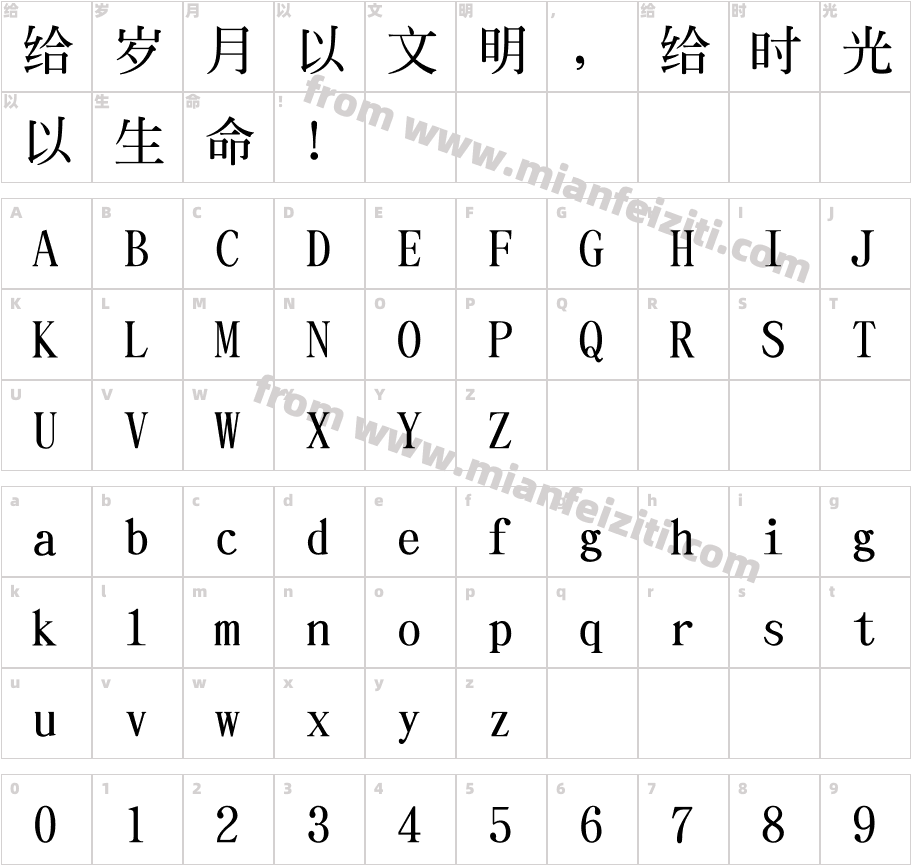
文鼎小标宋简繁(5.0版)
更新Power TrueType Version 5.0版,和原Power TrueType Version 4.0或Power TrueType Version 4.5版本相比又将原Power TrueType big5的扩展471个外字集的部分没有映射字码点的汉字进行了对号入座,并修复『㘭』字误映射到『抝』字位置的错误。
本款“文鼎小标宋简繁(5.0版)”是一款书写很新颖的字体,字体大方,适合各种设计作品使用!欢迎下载!